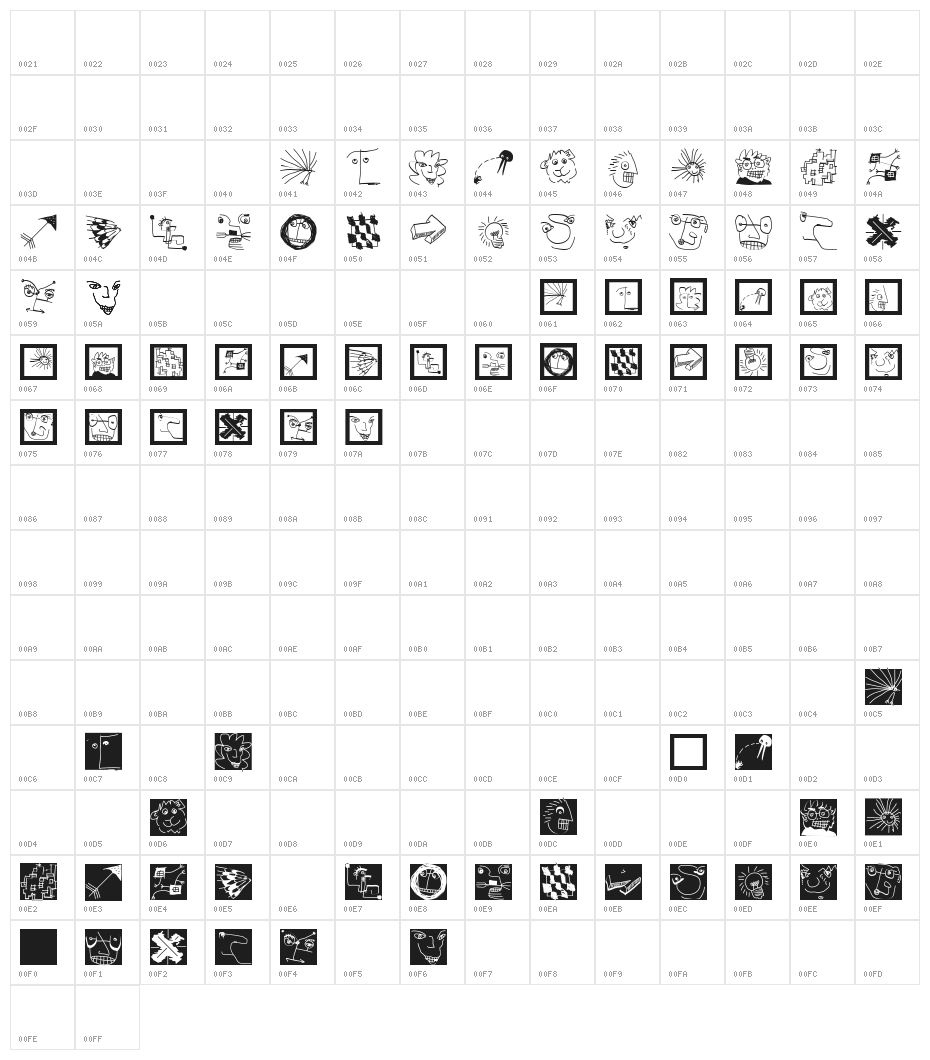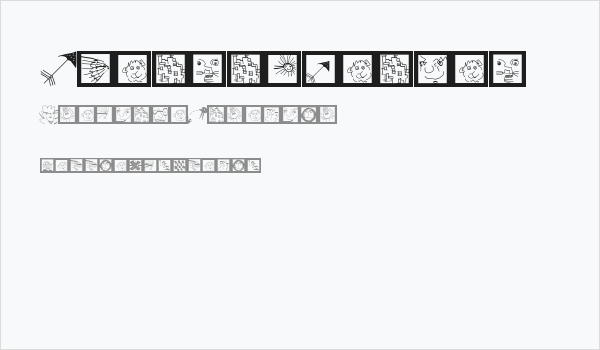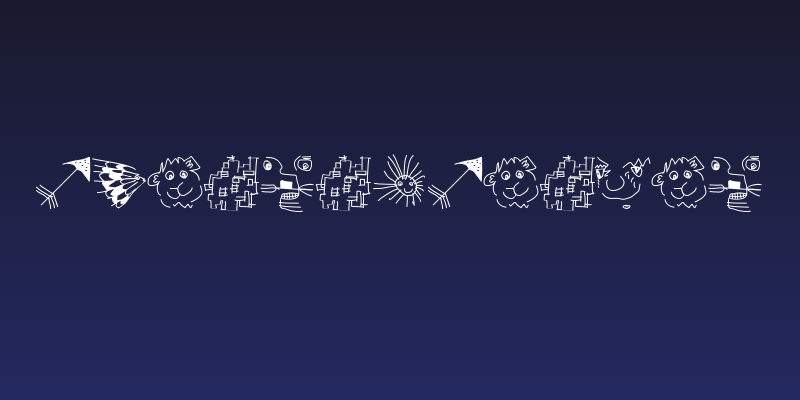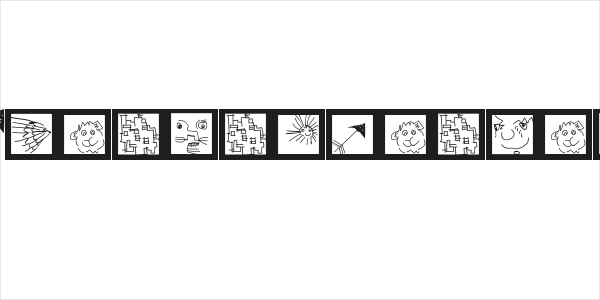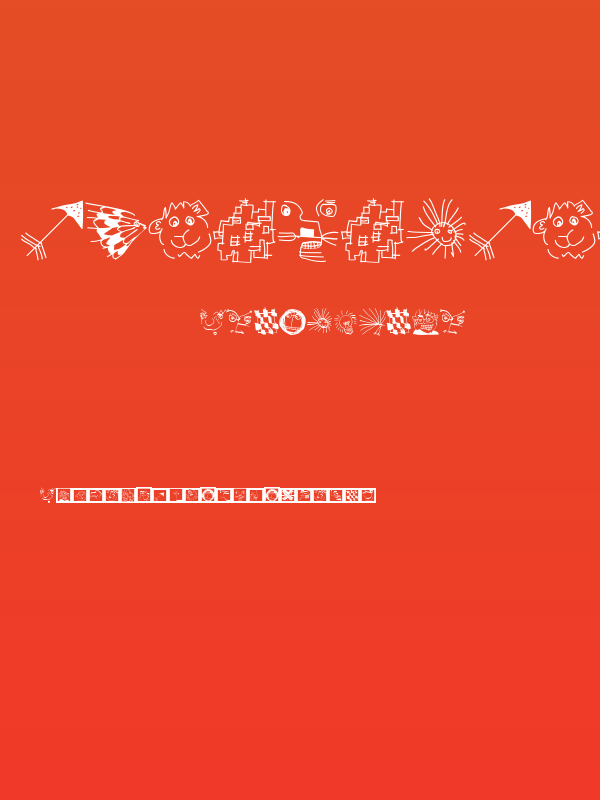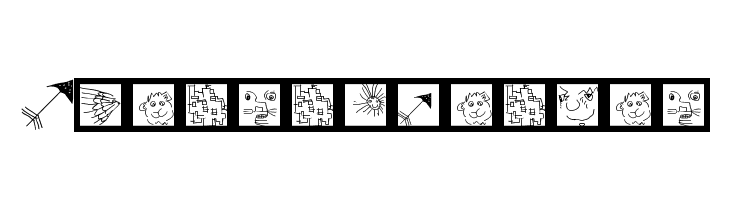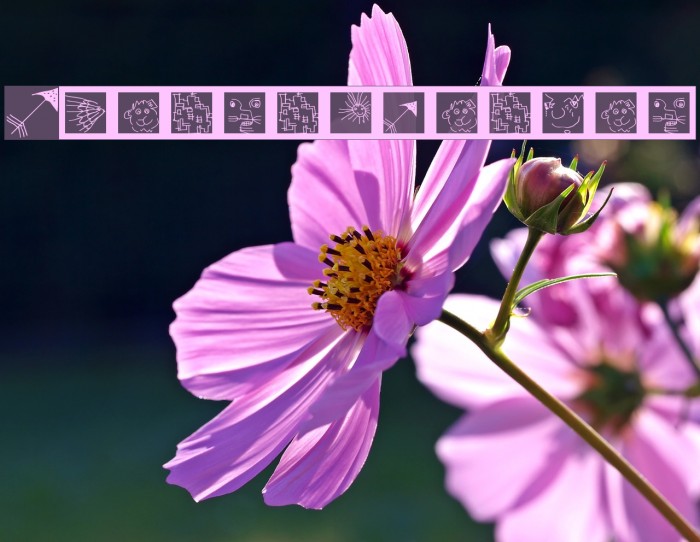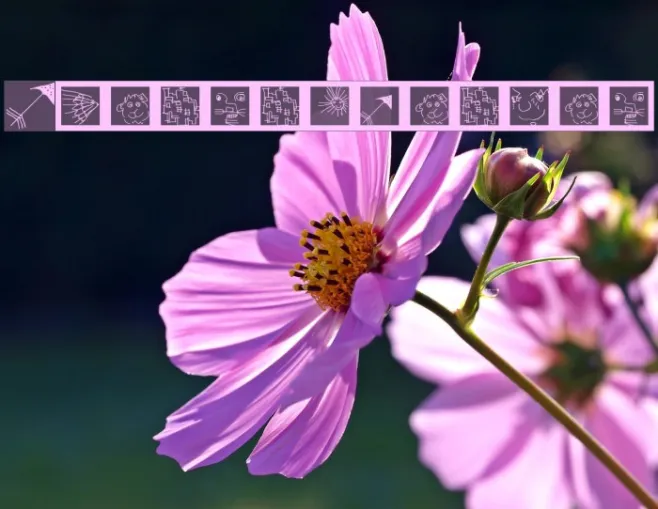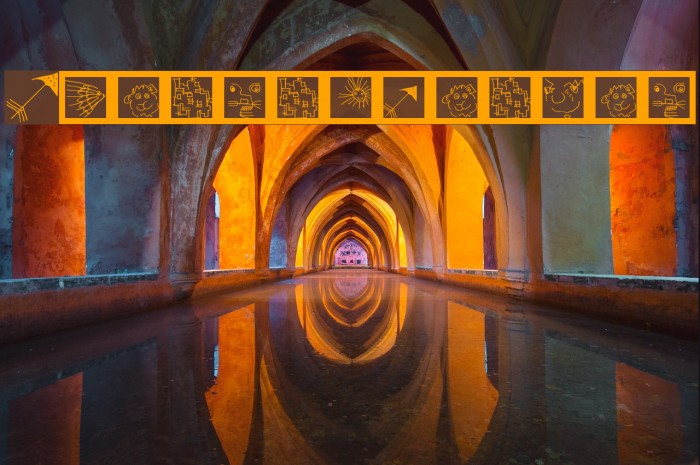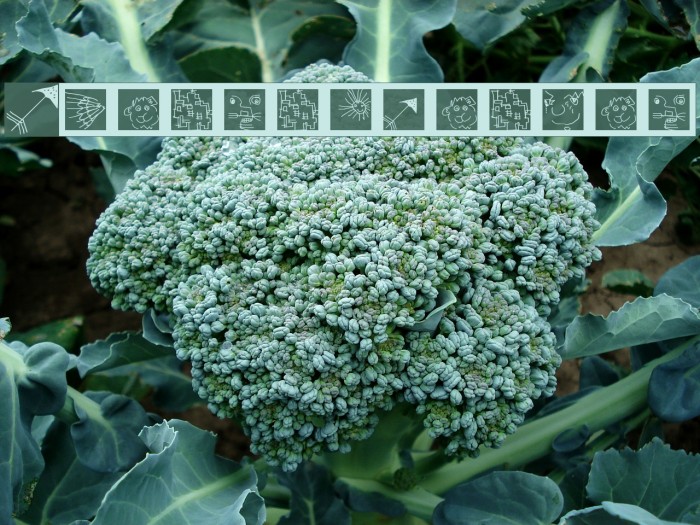
Kleinigkeiten Font
| Caso d'uso | Logos, Posters, Artistic Projects |
| Progetti proposti | Ideal for children's books, playful posters, creative invitations, and any project that benefits from a fun and artistic touch. |